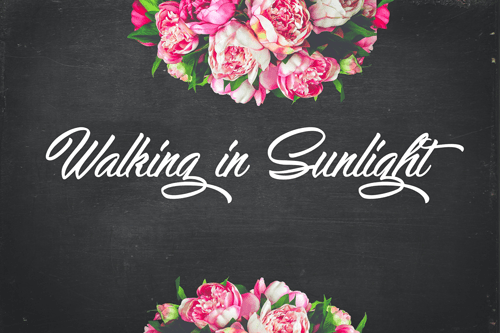
Walking in Sunlight Font – Download Grátis
A Walking in Sunlight Font é uma opção elegante para quem busca uma tipografia suave e envolvente, perfeita para projetos que valorizam a simplicidade do cotidiano. Oferecida como fonte de escrita artesanal da Octotype, essa família de fontes inclui um conjunto completo com licença comercial, disponível em . Com sua tipografia suave e arredondada, é uma escolha perfeita para gráficos que valorizam a harmonia entre letra e imagem. Esta fonte é ideal para criações de cartazes, editoriais de blog, logos personalizados ou qualquer outro projeto que deseje trazer um toque natural e poético à sua arte digital.